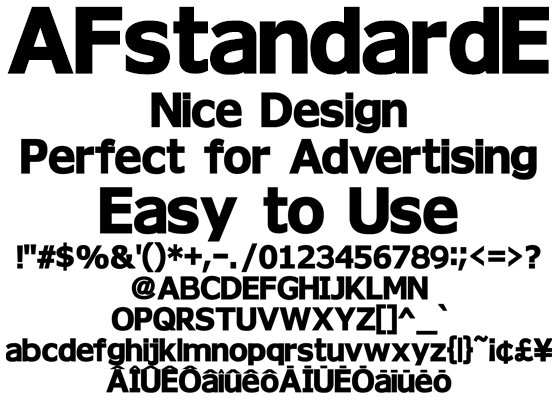
PR専用欧文 AFStandardE
AFStandardE
大文字と小文字のアセントを近づけ流れる読みやすさを実現しました。見慣れたデザインで読みやすい極太いゴシック体。強めのカーニングがリーフレットやお洒落なドキュメントに最適です。個人同人向けアニメ、動画向けなフォント。記号類、マクロンやサーカムフレックスなどのダイアクリティカルマーク追加。日本のローマ字表記で使われる訓令式やヘボン式で扱うÔやŌを収録、人名地名でもお使い頂けます。